Zoals ik in het vorige boekbindbericht al opmerkte, laat Anna Cairoli met haar eigen werk zien dat geen enkel materiaal taboe is. Vandaar dat ik me een beetje heb uitgeleefd toen Corrie me vroeg om een boekje te maken van teksten rond Martha en Maria uit het Nieuwe Testament.
In een groepje had men gesproken over de twee zussen en brieven geschreven vanuit het perspectief van elk van hen; er was ook wat inleidend materiaal. En er waren foto’s van wat de deelnemers bij de afsluitende bijeenkomst hadden meegenomen; één van die voorwerpen, het „duizend-dingen-doekje”, vormde een inspiratiebron.
Ik besloot elk onderdeel (algemene inleiding, theologische teksten, brieven van Martha, brieven van Maria, en foto’s) op een andere kleur papier af te drukken, gescheiden met grijze titelvellen. Dat vereiste hier en daar wat aan elkaar gelijmde pagina’s, maar meestal zou ik normale katernen kunnen gebruiken.
De band moest het verschil laten zien tussen de verzorgende, ronddravende Martha en de stilzittende, luisterende Maria. Martha zou worden vertegenwoordigd door een stuk theedoek met de letter M erop geborduurd, Maria door een stuk papier met een sierletter M.
Voor het materiaal ging ik naar Vlieger in Amsterdam. Daar kocht ik vijf kleuren papier voor de pagina’s, henneppapier voor de band, marmerpapier voor de schutbladen, roze linnen garen en kapitaalbandjes. Boekbindlinnen had ik niet nodig; ik kocht een fijne donkergrijze geruite katoenen theedoek bij Dille & Kamille in Utrecht.
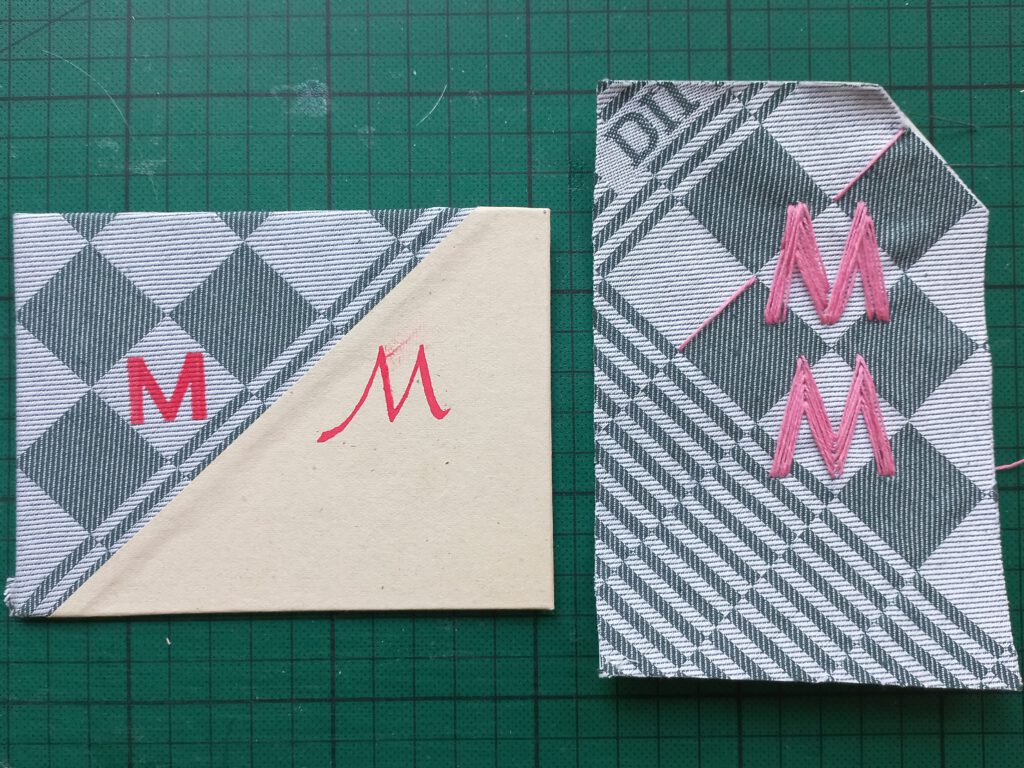
Eerst lijmde ik de theedoek op een vel stevig papier. Een katoenen doek is nogal rekbaar, dus ik lijmde het papier in (met behulp van een lakroller), legde daar voorzichtig de theedoek op en wreef die aan. Ik maakte een klein proefbord en schreef daarop de letters M met rode Posca-stift. Dat vond ik niet geweldig, dus probeerde ik het borduren van de letter M uit op een stuk theedoek-papier.
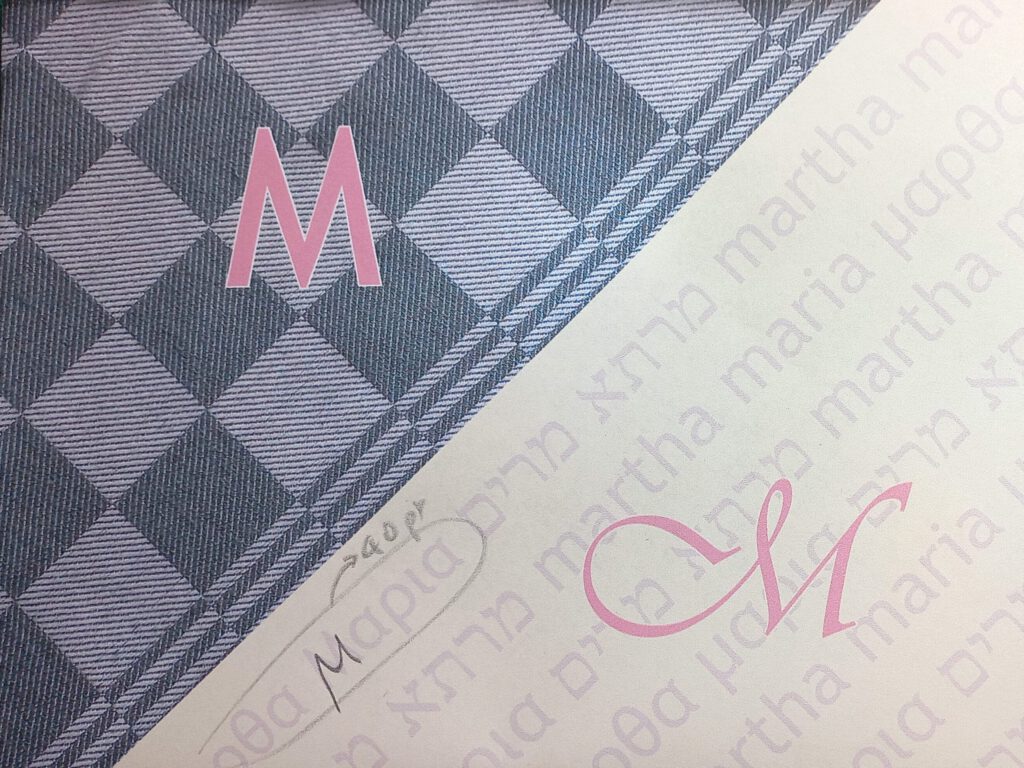
Ook maakte ik een proefdruk van de voorzijde van de band, om de layout precies goed te krijgen. Er bleken nog enkele correcties nodig in het tekstbestand. De titel zou groot op de voorkant komen, met daaronder, en op de achterkant, de namen Maria en Martha in Grieks, Hebreeuws en Latijns schrift.
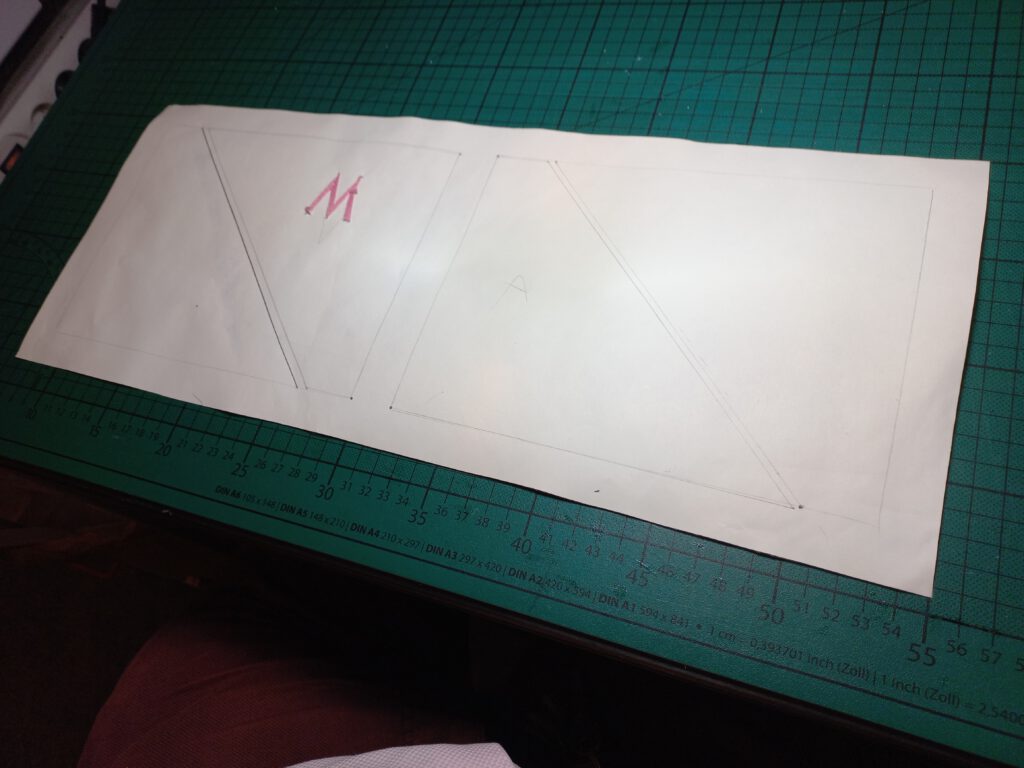
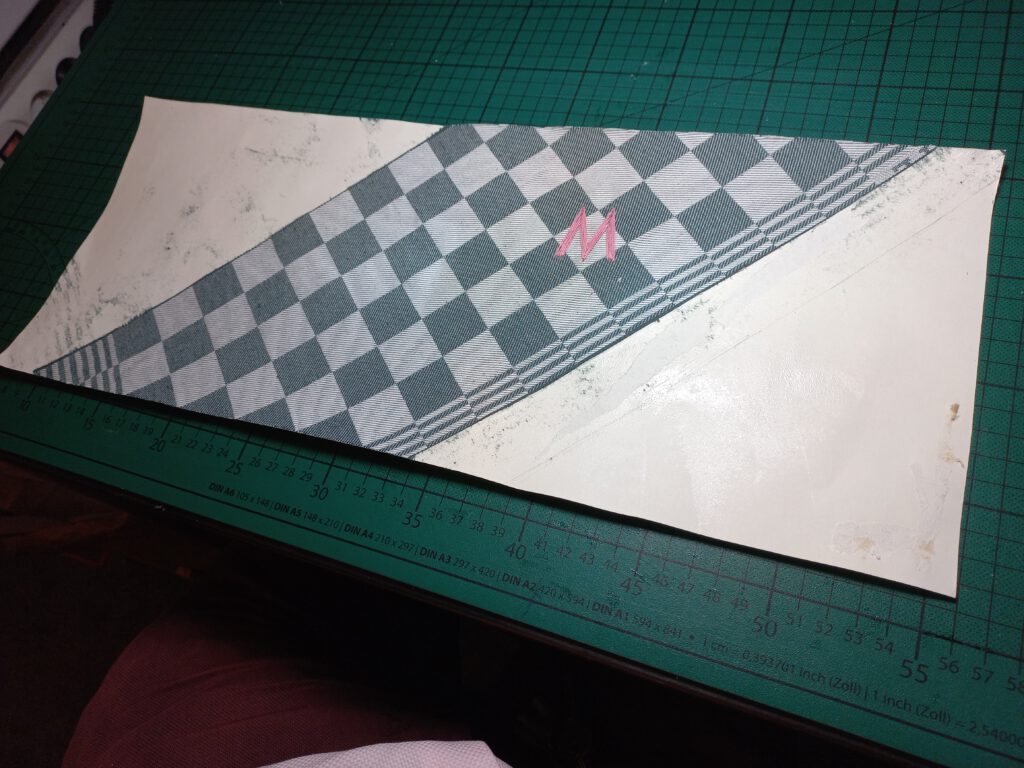
Van een op maat gesneden stuk van het theedoek-papier verwijderde ik de overtollige stukken theedoek. Daarna borduurde ik de M van Martha.
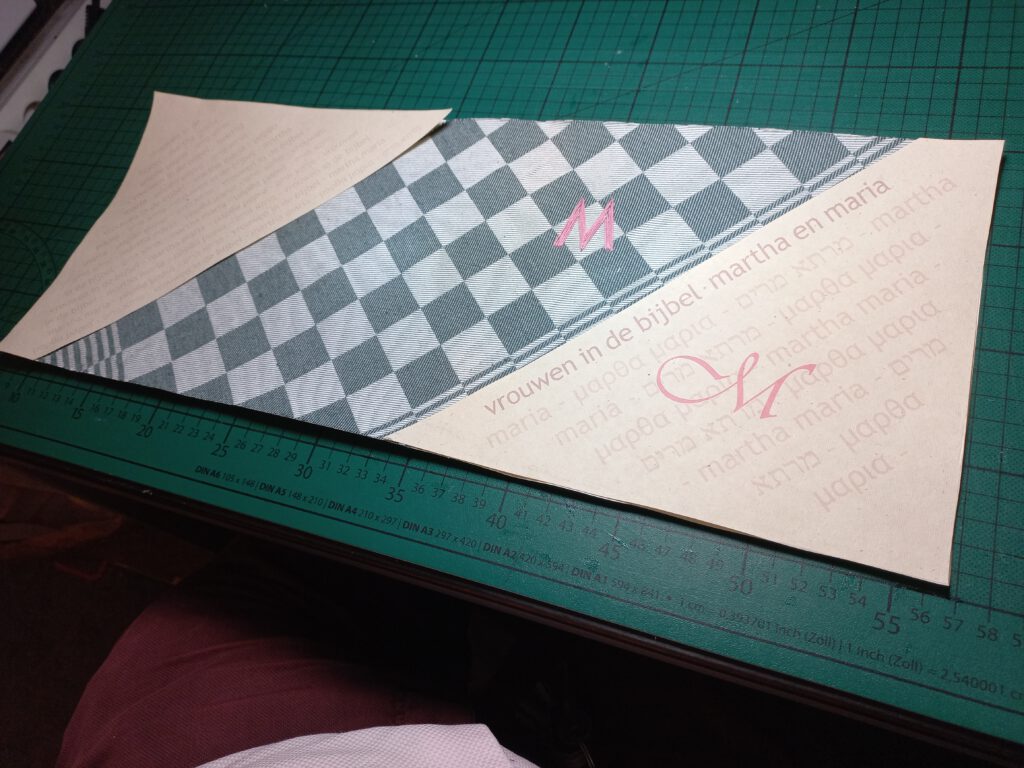
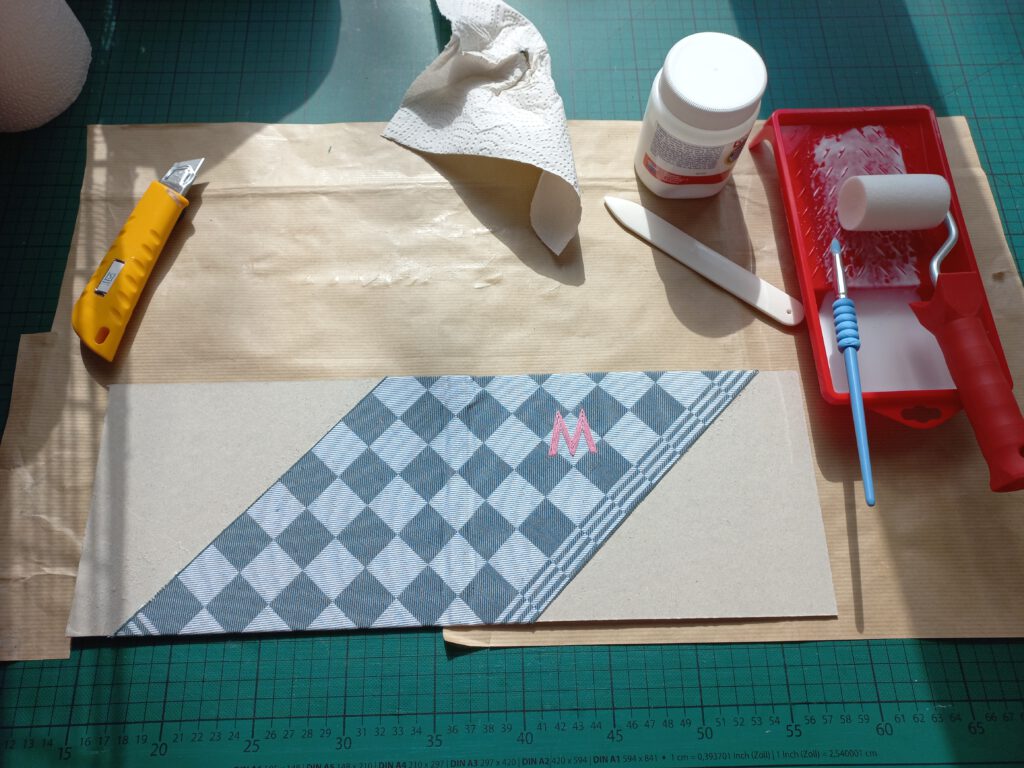
De basis van de band maakte ik zoals ik (opnieuw) geleerd had. Het geborduurde en op maat gesneden deel van het theedoek-papier lijmde ik over de rug en de helft van voor- en achterplat. Daarna lijmde ik de papieren voor- en achterdelen ongeveer 1 mm over het katoen heen.
Het veelkleurige boekblok, bij de Grafische Werkplaats Amsterdam bijgesneden, en daarna voorzien van schutvellen, gaas en kapitaaltjes hing ik in de band. Het geheel ging ’s avonds tussen twee plankjes met een paar kilo aan dumbbells er bovenop, en de volgende dag was het boekje klaar.